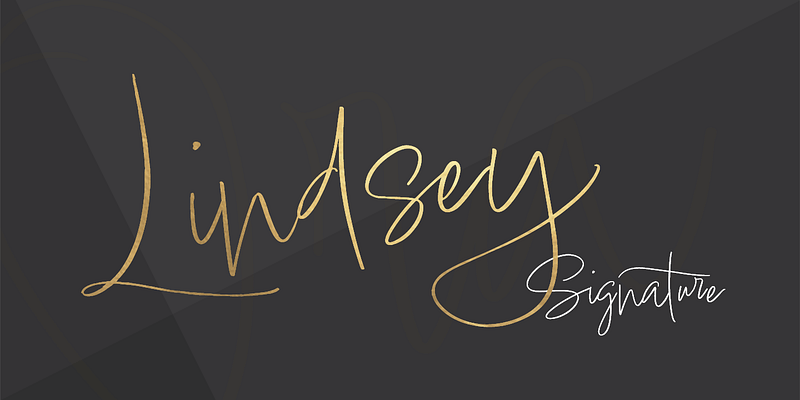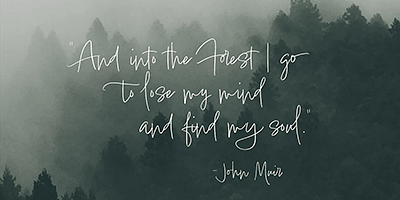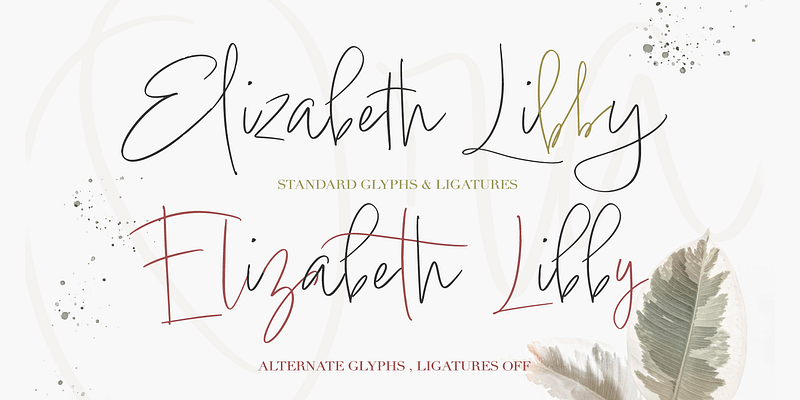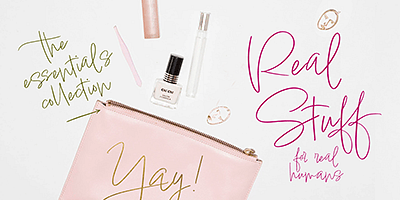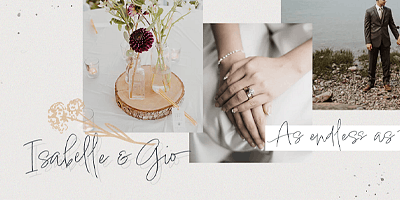
Lindsey Signature è un font di script casual che replica lo spirito della scrittura a mano naturale. Le caratteristiche di Opentype includono legature e glifi alternativi che aggiungono spontaneità e vivacità. Lindsey Signature è una scelta elegante per editoriali, pubblicità, campagne sui social media, lifestyle e collezioni di moda.
Caratteristiche: legature standard e discrezionali e glifi alternativi. Glifi bonus aggiuntivi accessibili tramite il pannello dei glifi.